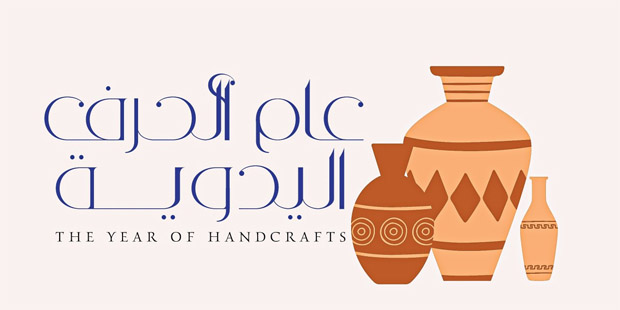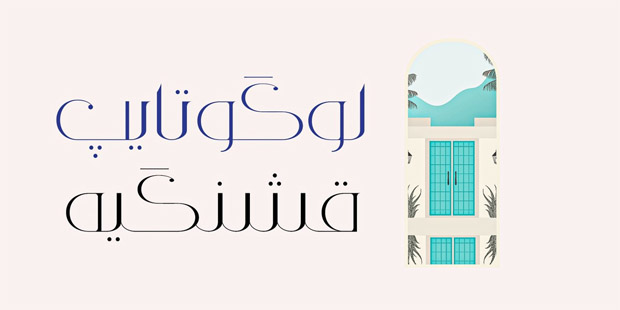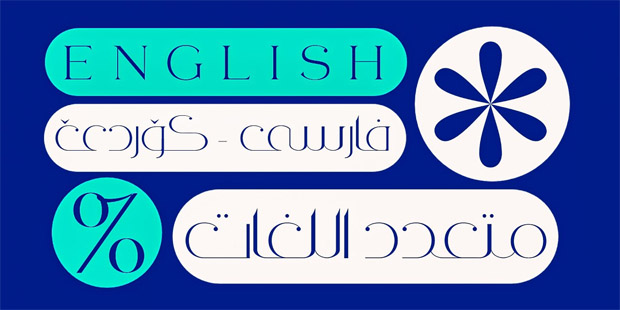
خط العرض زايرو الفني عربي فارسي لاتيني .. خط فني رائع متعدد اللغات حيث يدعم العربية والفارسية، كما يدعم اللغة الإنجليزية واللهجة الكردية، يمكن استخدامه في أعمال التصميم والدعاية والإعلان وهو ممتاز للعناوين الكبيرة.